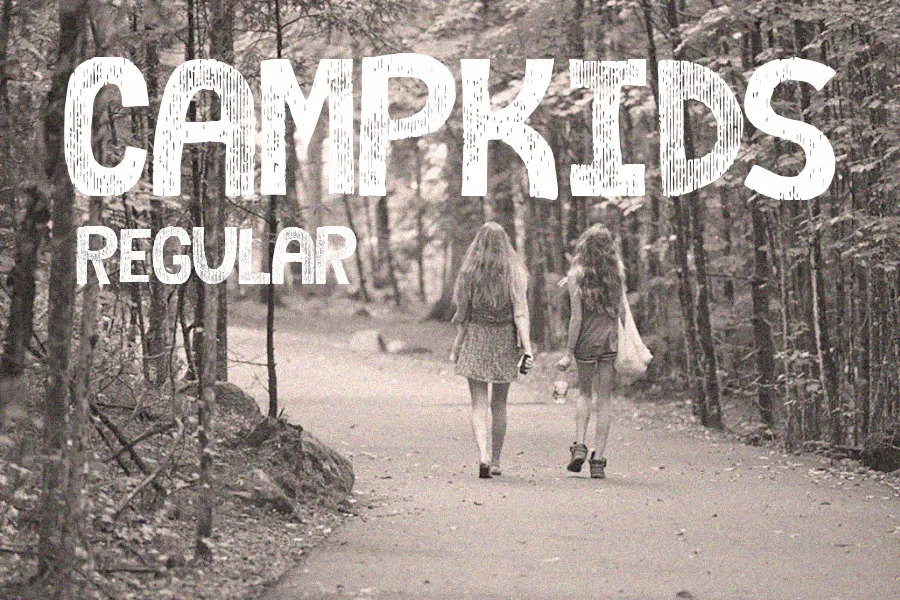
Camp Kids Font – Download Grátis
A fonte ‘Camp Kids Font’ foi criada por Hamilton para o público-alvo jovem e atrevido que busca uma fonte com alegria e leveza. Com formas redondas e imagens ilustrativas, essa fonte é perfeita para criações infantis ou projetos divertidos. Perfeita para atividades educacionais ou até mesmo como um recurso legal em sites de crianças, ela se destaca no mundo dos Display Fonts por sua capacidade única de transmitir uma energia positiva e criativa aos usuários. Seja você um designer gráfico ou simplesmente alguém que busca adicionar um toque único a seus projetos de escrita digital, esta font pode ser a solução perfeita para tornar seu trabalho ainda mais divertido e vibrante.